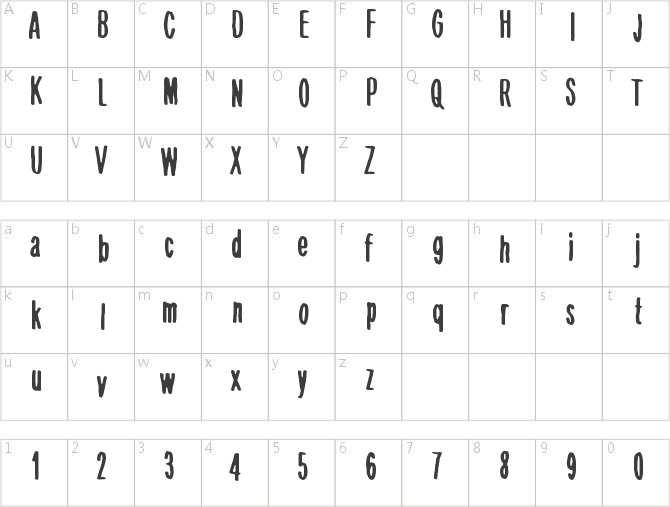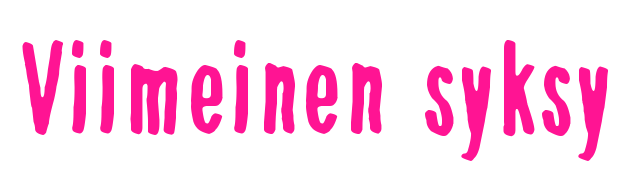
Viimeinen syksy 詳情頁
字體名稱: Viimein
Viimeinen syksy
Viimeinen syksy字體字庫是一款讓人賞心悅目、百看不厭的英文字體,適合各類廣告和產(chǎn)品包裝設計應用,字體大小0.03MB,格式為ttf字體,上傳用戶是東方時尚,作者/版權(quán)方為未知